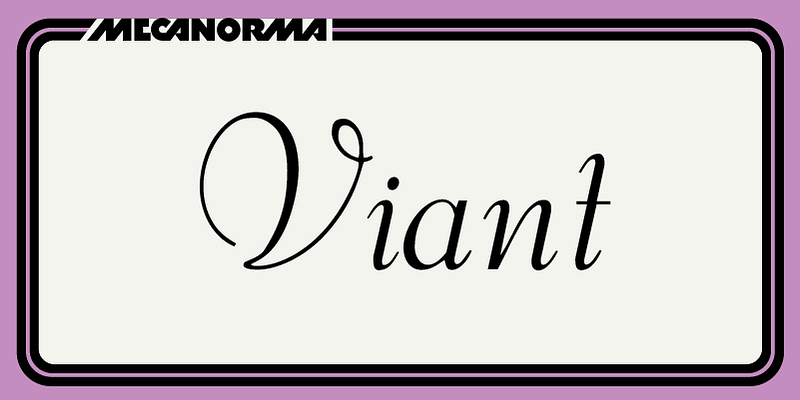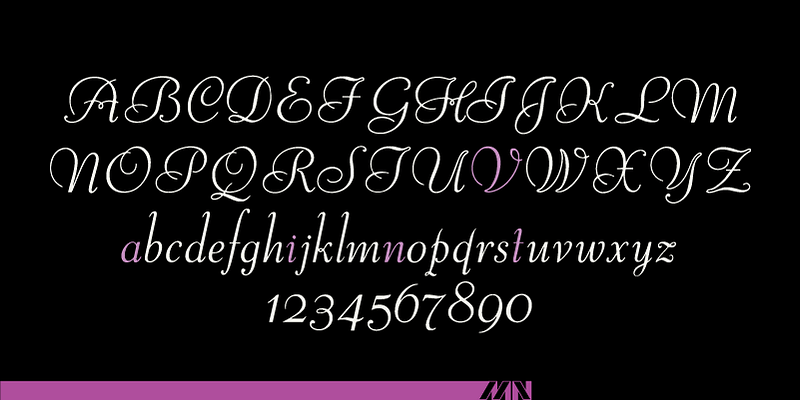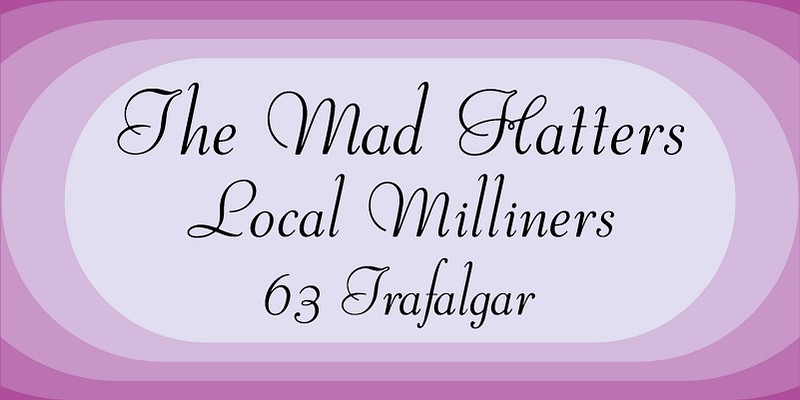
Das französische Unternehmen Mecanorma war einer der weltweit größten Anbieter von Transferschriften. 1995 zog sich Mecanorma aus dem professionellen Grafikmarkt zurück. Während dieser Zeit wurden die Transferschriftenprodukte von Trip Productions BV hergestellt. 2004 lizenzierte International TypeFounders (ITF) die digitalen Schriften von Trip Productions BV und veröffentlichte das Portfolio als Mecanorma Collection. Damit blieb eine der besten digitalen Schriftbibliotheken für Display-Schriften erhalten, die echtes Können und Handwerk mit modernen Tools verbindet. 2014 schloss ITF eine unwiderrufliche Vereinbarung mit den Nachfolgern von Trip Production. Diese Vereinbarung bestätigte die weltweiten exklusiven digitalen Rechte von ITF an der Sammlung.